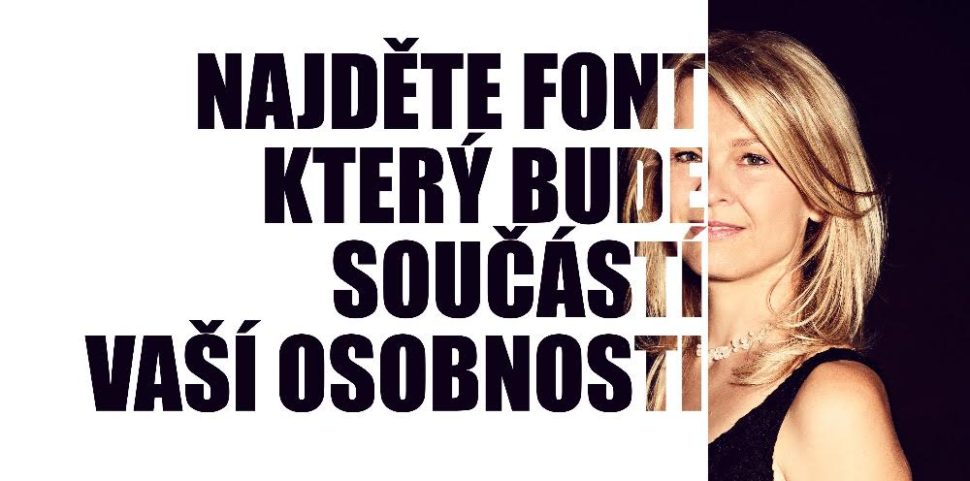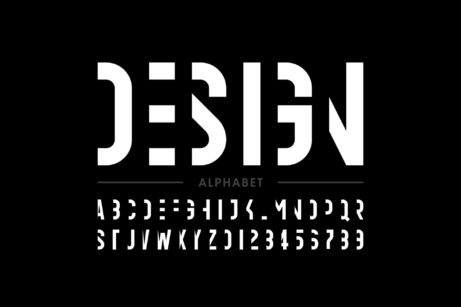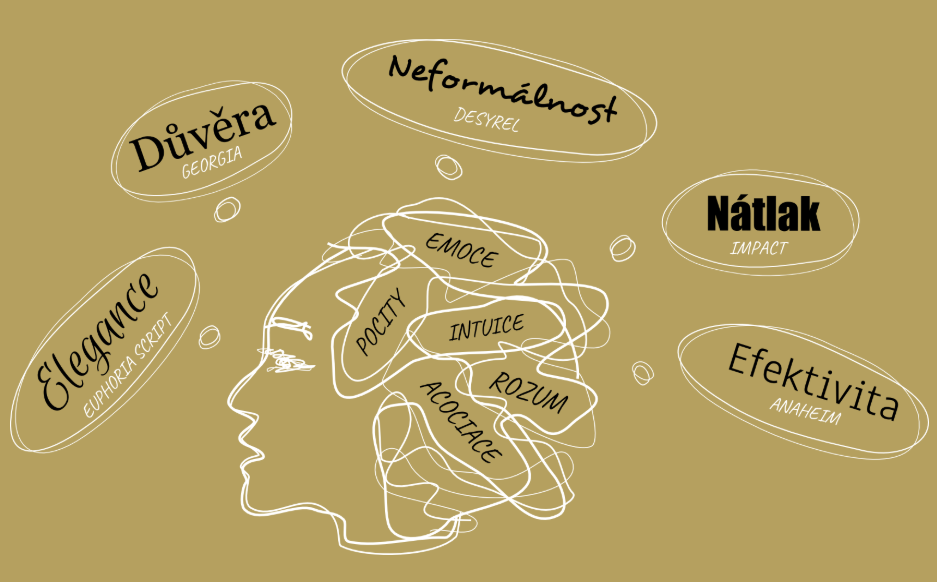
CO JE PSYCHOLOGIE FONTŮ?
Psychologie fontů je nový obor, který popisuje, jakým způsobem fonty ovlivňují vnímání textu.
FONTY, EMOCE A ASOCIACE
Vnímání fontů člověkem má svá pravidla a jejich výběrem předáváte jasné a konkrétní informace podvědomí čtenáře. Fonty na nás působí jak svým vzhledem, tak díky asociacím, které v nás probouzí.
FONTY A JEJICH VZHLED
V každém textu vnímáme tvary písmen, mezery mezi nimi i vzájemné proporce čar a křivek. To vše na nás působí a vyvolává ve vašem podvědomí reakci. Sklon písma, řád, křivky, to všechno je součástí vzhledu fontu a okamžitě ovlivňuje naše vnímání. A vzbudí emoce.
FONTY A NAŠE ASOCIACE
Co vás napadne jako první, při pohledu na tyto fonty? Psací stroj, školní docházka, osobní dopis nebo 2. světová válka? To jsou asociace, které má většina z nás. A které můžeme využít při výběru fontů. Asociace kulturní, historické, společenské nebo asociace spojené se silnou značkou.
FONTY V AKCI
FONT MŮŽE ZVÝŠIT ŠANCI VYHRÁT VOLBY
Různé psychologické působení fontů dobře znají i organizátoři politických kampaní. Podle The New York Times mohlo Baracku Obamovi v předvolebním klání pomoci také použití elegantního a svěžího fontu Gotham. Já se k New York Times připojuji a napsala jsem pro vás článek Font, který změnil historii >>>. Tipnete si, jaký font používá Donal Trump? Pobaví vás to. Možná je to spíš k pláči.
FONT MŮŽE ZVÝŠIT DŮVĚRYHODNOST AŽ O 30%
Baskervilský experiment provedl novinář E. Morris ve spolupráci s The New York Times v červnu roku 2015 a zúčastnilo se ho přes  45 000 respondentů. Wow, to je hodně lidí, že? Pokud to myslíte s marketingem vážně, i vás by mohly výsledky zajímat! Morris totiž přinesl odpověď na otázku: „Může font sám o sobě zásadně ovlivnit to, jak vnímáme obsah sdělení?“">> celý článek
KDE VŠUDE LZE PSYCHOLOGII FONTŮ VYUŽÍT?
Vnímání fontů člověkem má svá pravidla a jejich výběrem předáváte jasné a konkrétní informace podvědomí čtenáře. Fonty na nás působí jak svým vzhledem, tak díky asociacím, které v nás probouzí.
FONTY V MARKETINGU
Font sám o sobě má obrovskou moc ovlivnit vnímání čtenářů a tím to, jaké emoce text vzbudí. Je to nástroj, kterým vědomě dokážete ovlivnit dopad sdělení na konkrétní cílové skupiny.
FONTY V DESIGNU
grafika, webdesign, DTP
Fonty jsou spolu s barvou nejdůležitějším prvkem designu. Typografická a estetická pravidla jsou základem, který Psychologie fontů® obohacuje o práci s konkrétní cílovou skupinou. Stejně jako psychologie barev učí, jak sladit formu vizuální prezentace s obsahem.
FONTY & BRANDING
osobní i firemní
Font tvoří vizuální identitu značky. Vyvolá ta správná očekávání, odliší vás od konkurence. Pokud je charakter fontu v souladu s hodnotami značky, zvýší její důvěryhodnost v podvědomí klienta. Font je duší každého brandu.
FONTY PODLE OSOBNOSTI
Font je nedílnou součástí vizuální identity každého člověka a stojí za to si ho vybrat s jasným záměrem. Popíše váš charakter, hodnoty, nastavení vůči druhým. Je formou neverbální komunikace, která je často důležitější, než samotná slova.
ŘEKLI O PSYCHOLOGII FONTŮ
„Font, použitý na webu nebo na vizitce, vyjadřuje osobitost, ovlivňuje vnímání a dokresluje celkový dojem. Má moc přitáhnout ty správné klienty a odradit ty ostatní. Dovoluje vyjádřit atributy, jako je důvěra, jednoduchost, péče, něžnost nebo síla. Proto dává smysl věnovat volbě fontu stejnou pozornost jako výběru barev, ilustračních fotografií nebo sloganu. A proto považuji psychologii fontů za velmi užitečný marketingový nástroj. “